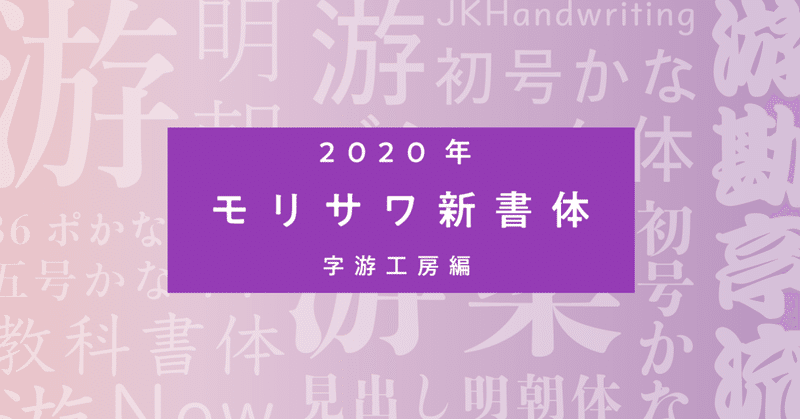
まだあります新書体2020〜字游工房書体全部みせ!〜
1. 字游工房について
有限会社字游工房は、本文書体や伝統的な書体を多く手掛け、ベーシックな書体の制作を得意とするフォントメーカーです。2019年3月1日より、モリサワのグループ会社となりました。
今回、字游工房の基幹書体ともいうべき「游明朝体」や「游ゴシック体」、大正時代の金属活字をベースにした「游築見出し明朝体」、太くうねりのある「游勘亭流」、かな書体としては情緒豊かな「游明朝体五号かな」「游明朝体36ポかな」など、組版の表情が広がる様々な書体がラインナップに加わります。
それでは、各書体についてじっくりみていきましょう!
2. 游明朝体
「游明朝体」は “時代小説が組めるような明朝体” をキーワードに開発された、落ち着きのある明朝体ファミリーです。文字の空間が均一に見えるような設計や柔らかな曲線が、明るく品のある雰囲気を演出します。
また、長時間見ていても疲れないように、点の起筆、ハライの先端、ハネの先端などを丸く処理しています。同様の理由で横画の終筆のウロコなどにも丸みがあります。
このような細やかな処理が明るく品のある雰囲気を演出しているんです!
ウエイトで展開は、“L・R・M・D・B・E” の6つですが、見出しに特化した “B” と “E” は他のウエイトと骨格が異なり、ふところが狭く引き締まったデザインになっています。この違いについて、担当デザイナーの鳥海修さんは開発当時、こう語っています。
読むことが主体の本文用書体に対して、見出し用書体は見る要素が強くなります。つまり見る人にある程度のインパクトを与える必要があります。
そうした要件を満たすために、漢字においてはつき出し(注)を付けるなど、一点一画をしっかり見せる処理をしました。同時に仮名においても、ベーシックという路線を踏襲しながら、ある程度主張すべく、力強いエレメントと引き締まった骨格を持たせ、若干小さくデザインすることによって、本文用とは必然的にデザインが異なりました。
《引用者注》つき出し:ここでは横画と接する縦画の起筆にある装飾のこと
《引用》游明朝体 E開発ノートより
3. 游築見出し明朝体
「游築見出し明朝体」は、大正時代の金属活字をベースに制作された伝統的な見出し明朝体です。当時の職人の手によってひと文字ずつ彫られた字形が尊重されており、大らかな印象を与えます。
明朝体の伝統的なデザイン処理である “はちやね“ や “ひっかけ” を積極的に採用するなど、当時の作風を踏襲しつつも、昨今の利用に耐えうるデジタルフォントとして丁寧にリファインされています。
このように、装丁やエディトリアルデザインのタイトルなど、見出しとして効果を上げる書体です。
また、OpenTypeフォントの字形切り替え機能が利用できない場合でも異体字が使えるように、 異体字のみをマッピングしたフォント「游築見出し明朝体 Alt」も同時に提供しています。
並べてみると、デザインが違うのがわかりますよね。
ぜひ、場面に合わせて使い分けて味わいを感じてみてください。
4. 游ゴシック体
「游ゴシック体」は、長文でも読みやすいスタンダードなゴシック体ファミリーです。 字面を小さめに設計し文字間にゆとりを持たせているので、小サイズで組んだときも一字一字が識別しやすく、 読みやすい組版を実現します。
商業印刷などの高精細な環境でも目にやさしくうつるように、エレメントに小さな丸みをもたせたり、打ち込みやハライに筆のイメージを残すことで、 柔らかく穏やかで、誠実な表情を演出できるゴシック体になっています。
エレメントの丸みについてはルールがあるようで...
こちらも「游明朝体」と同じく開発ノートで詳しく解説されています。
7つのウエイトで構成され、キャプション・本文から小見出し・大見出しまで幅広い用途に対応します。
なかでも “L” は特殊な位置づけで、見出し用としても本文用としても使える使用範囲の広い書体です。オーソドックスな骨格、極細の線幅、なめらかな線質は、繊細な雰囲気を醸し出します。
5. 游教科書体 New・JKHandwriting
「游教科書体 New」と「JKHandwriting」は、東京書籍株式会社と共同開発された書体です。それぞれの特徴をみていきましょう!
「游教科書体 New」は、筆順や筆法など、教育現場で求められる条件を満たす教科書体です。 縦画と横画の太さの差が少なく、簡潔で穏やかな筆の運びになっています。
国語や書写に適した縦組み用と、算数や理科に適した横組み用の2種類のフォントが提供されるのも特徴のひとつです。
それぞれの仮名を比べてみました。
縦組み用の仮名は、書写の書き文字に準じて仮名のもつ固有の形を尊重しつつ、読みやすさを損なわないようにデザインされています。
一方横組み用の仮名は、算数や理科、社会などで算用数字と混ぜて使われることが多いため、漢字、仮名、数字がバランスよく並ぶように、仮名の大きさを揃えているんです。
こうして背景がわかると、用途に応じて使い分けてみたいなって思いますよね。ここで、教材作りに役立つフォントをもうひとつ。
「JKHandwriting」は、甲南女子大学の准教授村上加代子さんのアドバイスを受け、開発された欧文書体です。
筆記用具にならった親しみやすい丸ゴシックタイプのエレメントで、初めて英語を学ぶ児童にも 学びやすいデザインになっています。また、弱視の児童に配慮した字形を採用するなどの工夫も取り入れられています。
5段階のウエイトに加え、イタリック体、4線付通常フォント・4線付なぞり書き用フォントの合計8書体が提供され、学校での教材作りなどを助けます。
4線付を手書きで引くのは、手間がかかりませんか?そんな時はぜひ「JKHandwriting」を思い出していただければと思います。
6. 游勘亭流
「游勘亭流」は、勘亭流の特徴でもある太くうねりのある運筆を継承しながら、 読みやすさも意識してアレンジされた書体です。
勘亭流:
江戸時代に作られた歌舞伎の看板などに書かれる、伝統的な肉太の縁起文字
実はモリサワのライブラリーにも「勘亭流」がありまして、並べてみると結構違うのがわかります。
ひらがなの “う” は「游勘亭流」の方がよりうねった形になっていたり、一見同じに思える勘亭流の中にもデザインのバリエーションがあるというのがおもしろいですよね。奥が深そうです。
歌舞伎っぽく組んでみました。ちなみに、たっぷりとした太さの由来は、歌舞伎の公演にお客さんが隙間なく入るようにとの願いがこめられたもの、ということだそうですよ!
7. 表情豊かな「かな書体」
左上から、「游明朝体五号かな」「游明朝体36ポかな」「游築初号かな」「游ゴシック体初号かな」です。
では、それぞれの特徴についてみていきます。
4書体いっきにご紹介しますので、ついてきてくださいね!
「游明朝体五号かな」は、明治時代に制作された本文向けサイズの金属活字をベースにつくられたかな書体です。 游明朝体の標準かなより字面が少し大きく、ゆったりとした柔和な線が特徴です
「游明朝体36ポかな」は、五号かなより少しあと、大正時代に制作された見出し向けサイズの金属活字をベースにデザインしたクラシカルなかな書体です。毛筆の表現力を活かした表情豊かな線と、独特のスタイルを持った字形が大きな特徴です。
この2書体は、游明朝体の漢字と組み合わせることを想定しています。
「游明朝体五号かな」は見出しや雑誌の本文を古典的で穏やかな表情に、「游明朝体36ポかな」はタイトルや見出しなど大きなサイズで使うことで、その個性がより一層引き立ちます。
「游築初号かな」は明治・大正時代の金属活字をベースにデザインした、見出し用のかな書体で、 「游築見出し明朝体」の漢字と合わせて使えるように設計されています。
「游築見出し明朝体」のかなと比べて太く、どっしりとした重厚感が特徴で、一部の字種に “異体字” が搭載されているのもポイントです。
「游ゴシック体初号かな」は、金属活字時代を代表するクラシックなゴシック体をベースにデザインされたかな書体です。名前の通り、游ゴシック体との組み合わせを想定しています。
表情の違うかなや明朝体風にアレンジされた句読点や記号類が、「游ゴシック体」のベーシックな印象の組版にまた違った表情を生み出します。
4書体それぞれ、字游工房書体の漢字と組み合わせることによって、さらに表現の幅が広がります。ぜひその表情の違いを試してみてください。